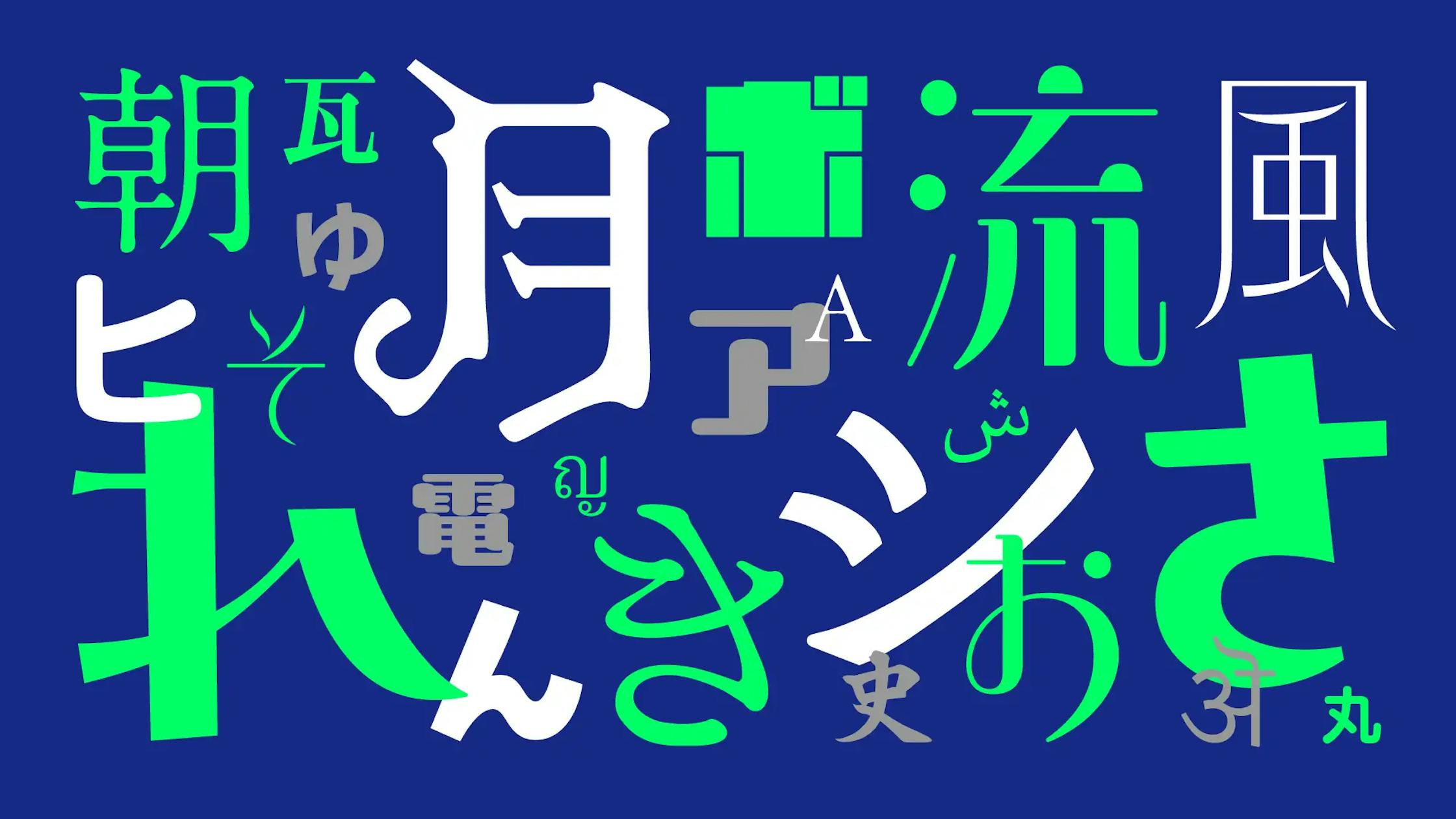
モリサワが2023年新書体をMorisawa FontsとMORISAWA PASSPORT製品で提供開始
株式会社モリサワは、2023年10月18日(水)より、契約中のユーザーに対して「アップグレード2023年10月版」を提供開始すると発表しました。このアップグレードにより、新たに262書体が登場します。主なアップデート内容は以下の通りです。
• 「A1明朝(AP版)」が3ウエイトかつ欧文を一新してリニューアル
• 「UD新ゴ コンデンス」のAP版が登場
• 従来のA-OTF書体はAP版書体化、A-OTFかな書体は総合書体化され、和文・欧文ペアカーニングと最新のIVSに対応した書体に
• 個性派書体「ボルクロイド」「月下香」「アルデオ」「つぶてん」に加え、レトロな雰囲気の新書体「プフ サワー」「プフ ソワレ」などが登場
• 「美風」「翠流きら星」「翠流ゆゆポップ」など台湾の繁体字フォントベースの新書体、また「瓦明朝」や「史仙堂楷書体」などがリリース
• 「ヒラギノ丸ゴ」にウエイト追加
• 欧文フォント「Lutes UD」シリーズにタイ文字、アラビア文字、デヴァナーガリー文字を展開